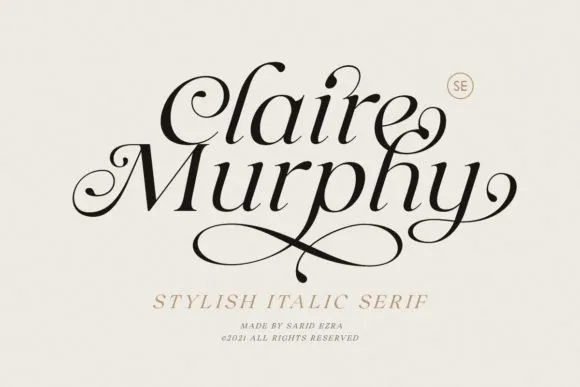
A fonte ‘Claire Murphy’ é uma elegante serif que oferece ao designer a oportunidade de criar tanto elementos modernos quanto nostálgicos para aplicações variadas, como logomarcas, revistas e mídia social. Foi criada pelo font designer saridezra em 99designs, um ambiente popular entre designers e empresas buscando novas soluções gráficas. Suas características flexíveis e estilos limpos certamente enriquecerão qualquer projeto. A função PUA (Portable User Access) permite que você acesse com facilidade todos os guionários e swashes da fonte, o que oferece um amplo espectro de possibilidades para inovar e explorar suas infinitas variações. Com seu estilo único, você pode usar esta fonte para tornar seus projetos ainda mais memoráveis.